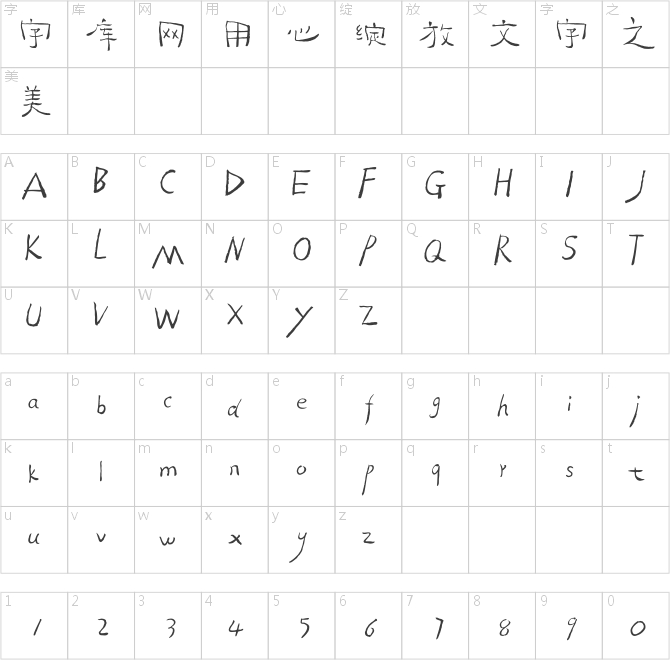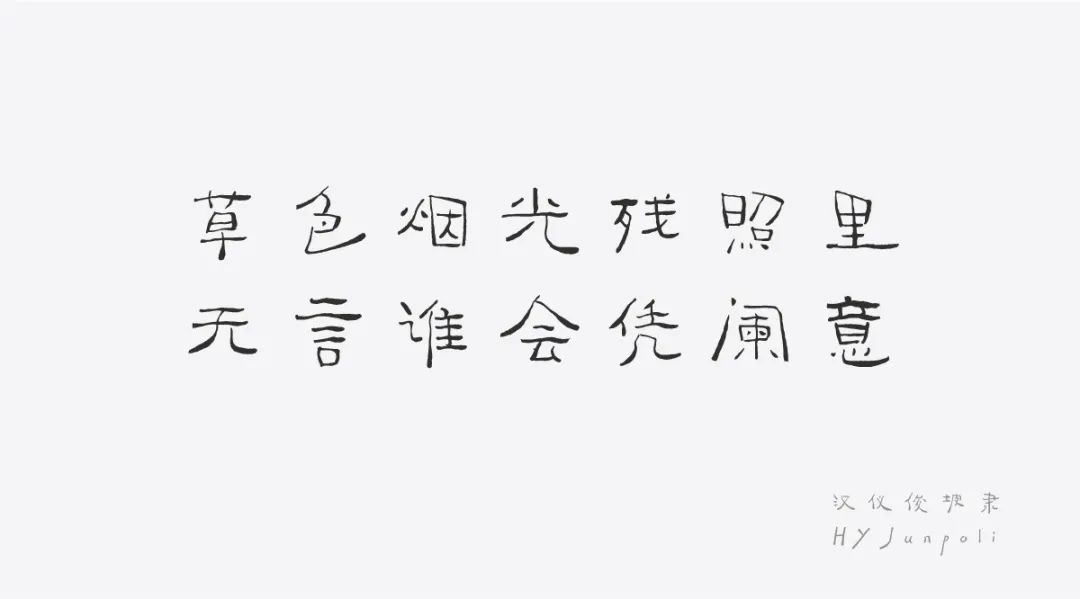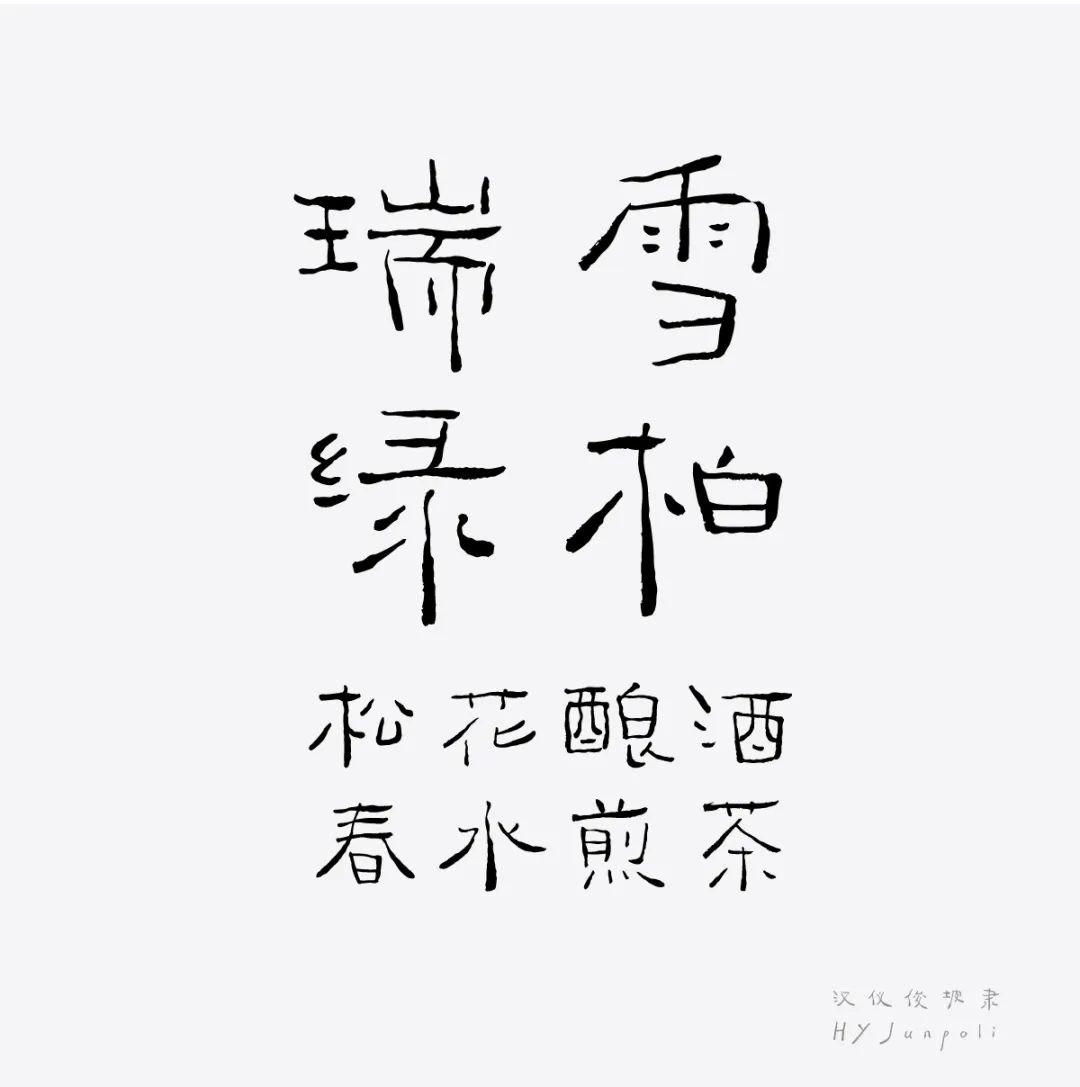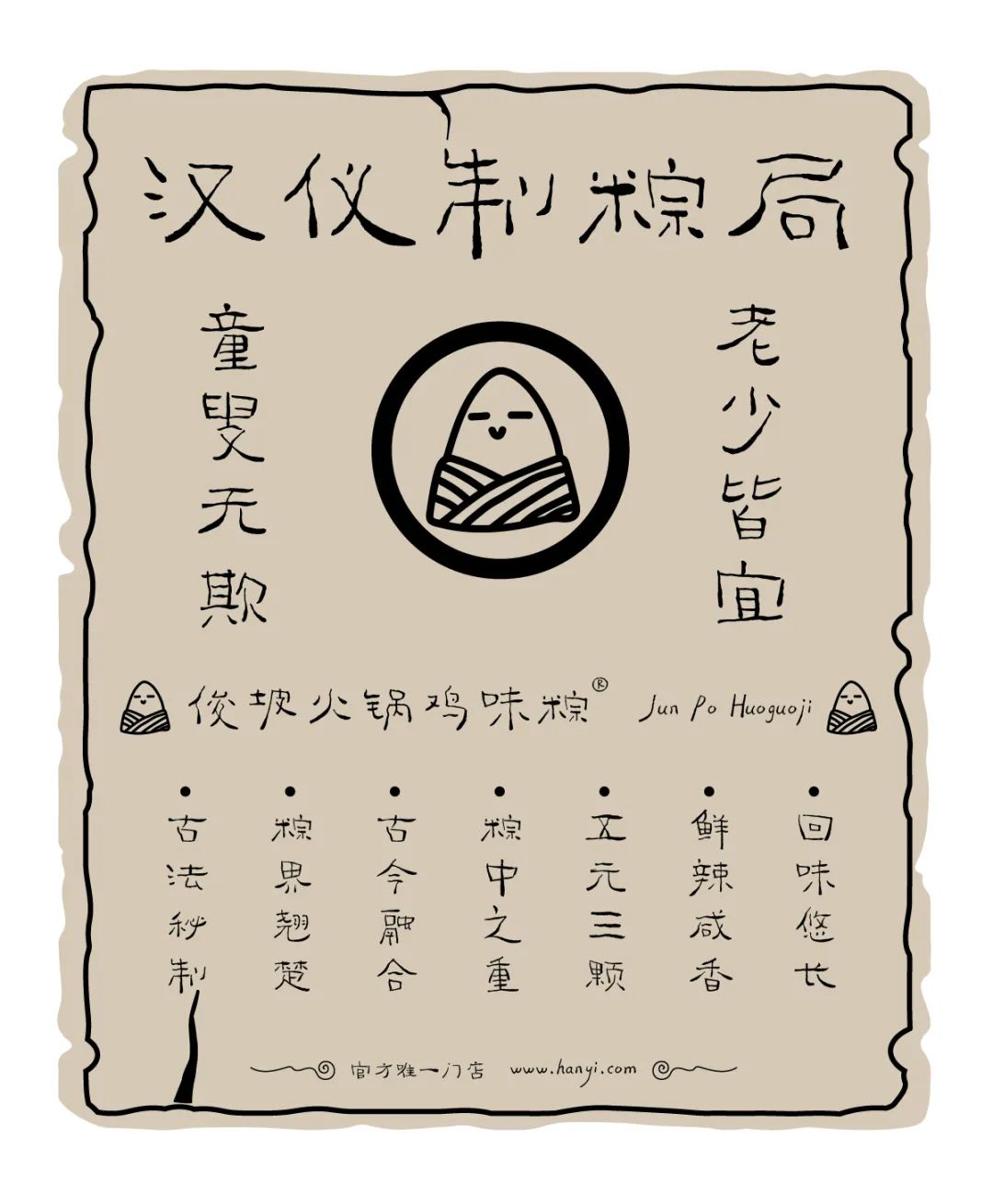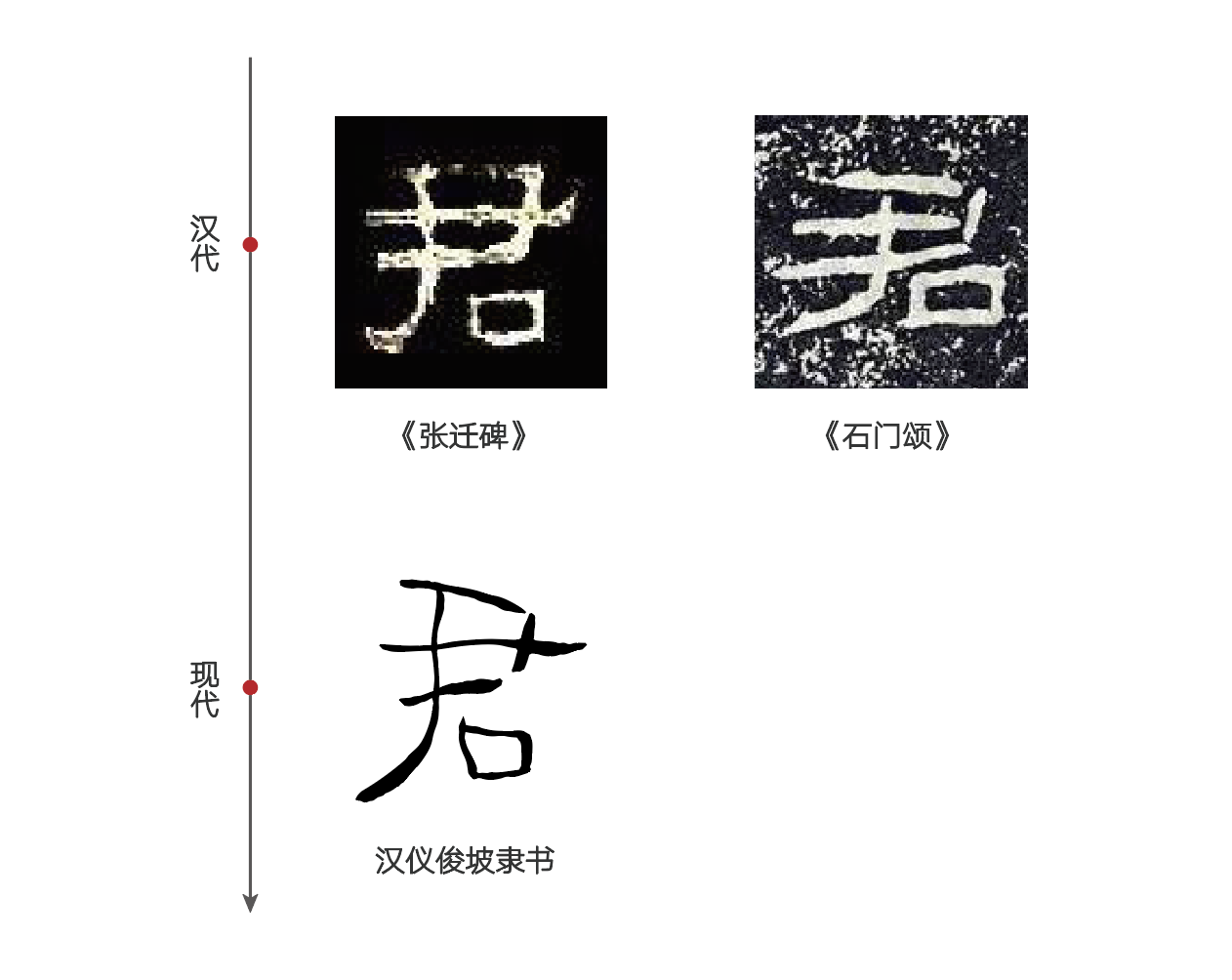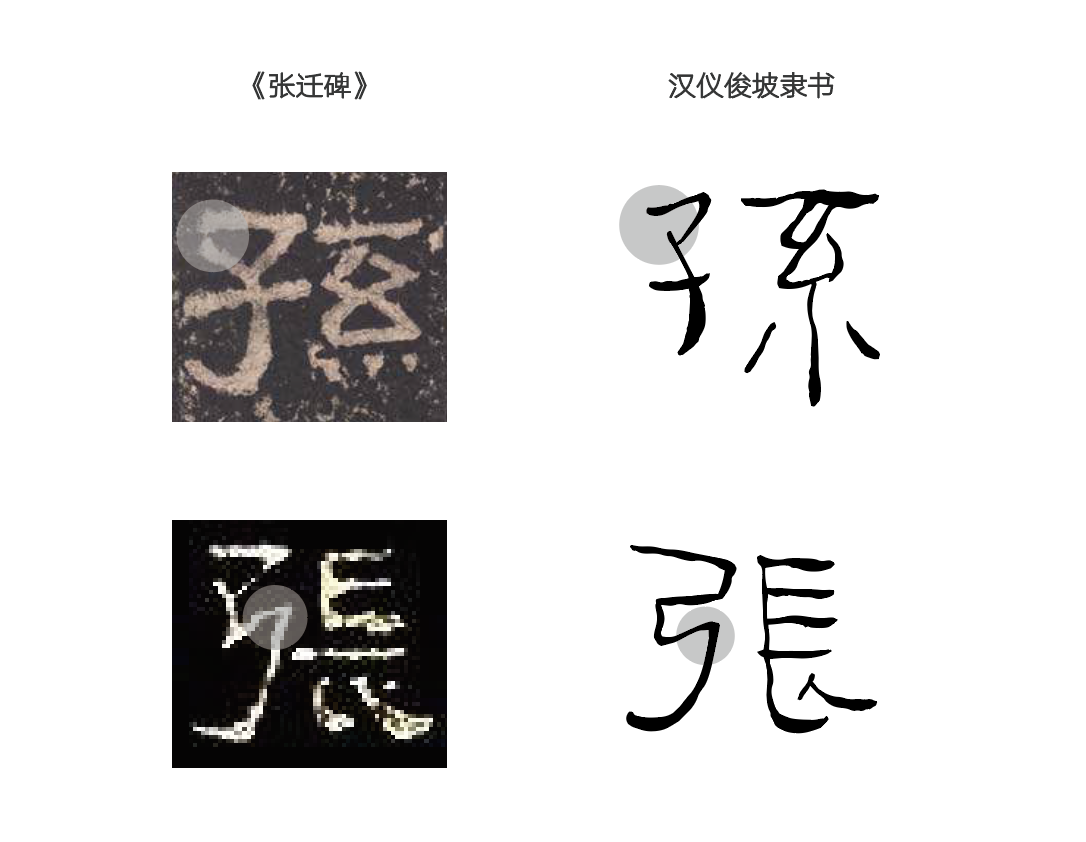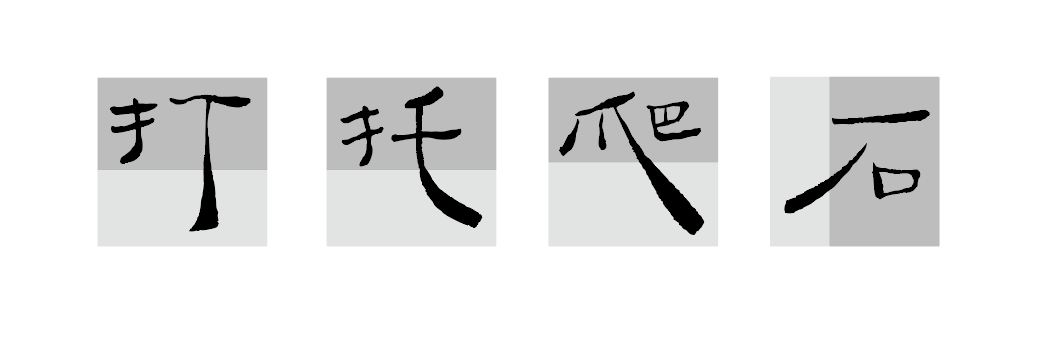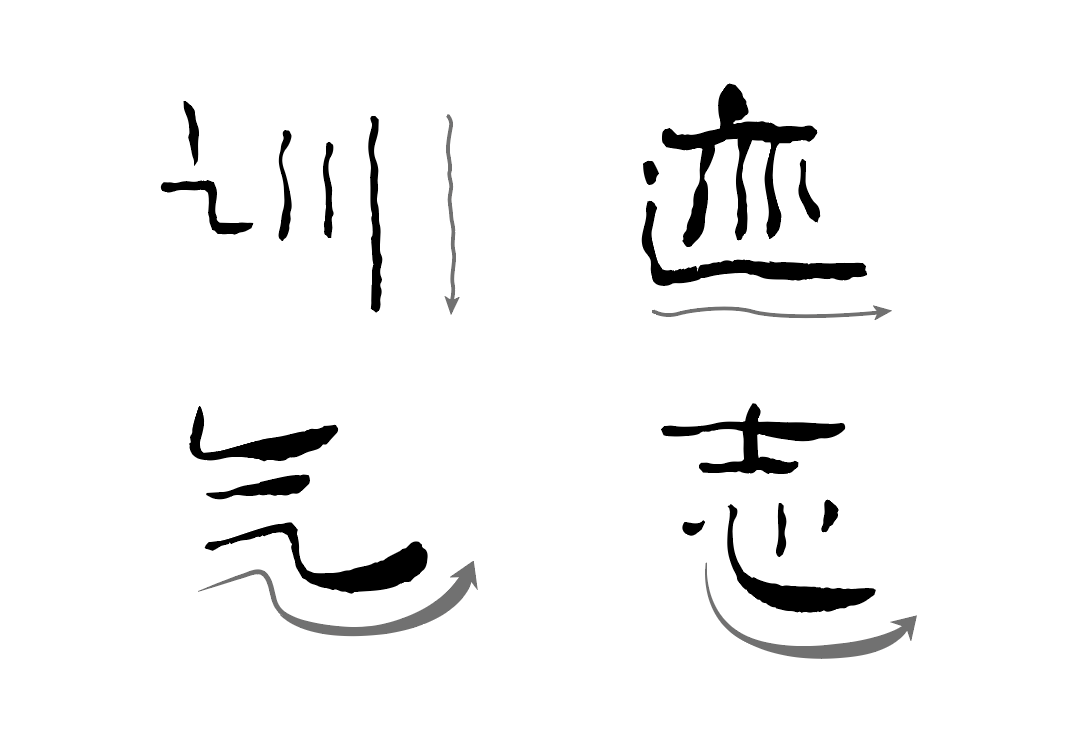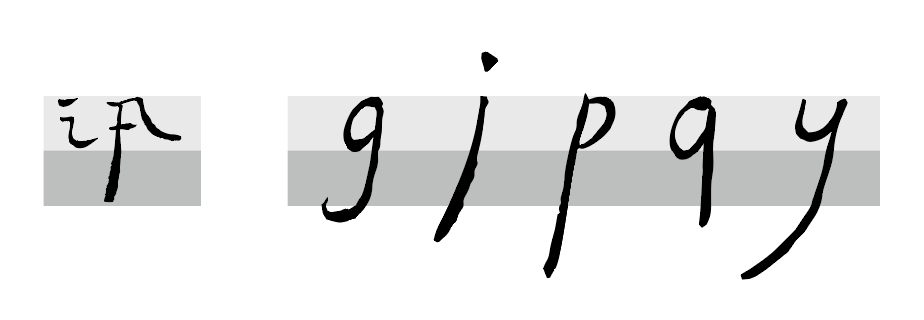
漢儀俊坡隸W 詳情頁
“漢儀俊坡隸書”是一款帶有濃郁古拙意味的隸書作品。它是由著名的簡牘書法家劉俊坡傾力書寫創作而成。“漢儀俊坡隸書”的誕生,不僅重新喚醒了簡牘背后的民族記憶,更闡釋傳承一個民族的光榮與夢想。
“漢儀俊坡隸書”以漢代《張遷碑》和《石門頌》結體為構字基礎,形成書風端正樸茂、結體巧妙大方,既有漢代廟堂遺韻,又含現代漢字審美的浪漫氣息。
“漢儀俊坡隸書”以簡牘墨跡的蝌蚪法和玉箸法為書寫造型元素,字體內斂外放,典雅自然,有著含蓄蘊藉的審美情趣。
“漢儀俊坡隸書”的寫法參考和保留了《張遷碑》的處理方式,還原了字體簡單淳樸的韻味。
漢儀俊坡隸書 | 筆畫特點 “漢儀俊坡隸書”筆畫拖長似飄帶狀,字體顯得靈動飄逸,結構疏密對比明顯。這樣的處理方式,打破了字體在演變過程中的僵化與呆板,賦予字體以靈性。 “漢儀俊坡隸書”筆畫提按過渡明顯,線條靈動活潑,粗細相間,賦予字體強烈的畫面感,整體效果顯得沉雄厚重。 漢儀俊坡隸書 | 中西文匹配 “漢儀俊坡隸書”西文字母充分吸收了中文結構,筆畫和線條的特點,形成了帶有古拙韻味的字母。中、西文搭配使用時呈現出更佳的視覺效果。 “漢儀俊坡隸書”西文字母提取了中文字體筆畫的部分處理方式。降低了字母下緣線的位置,拉長了筆畫結構。 漢儀俊坡隸書 | 字體展示